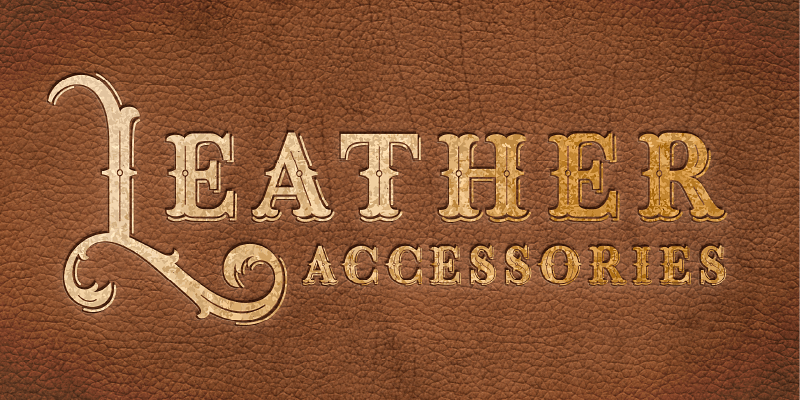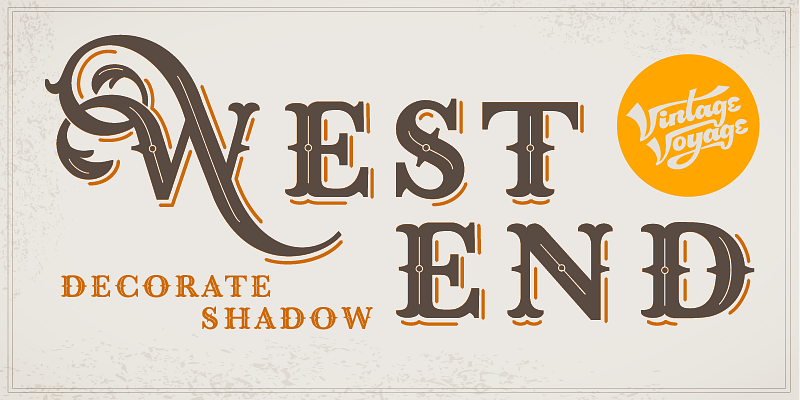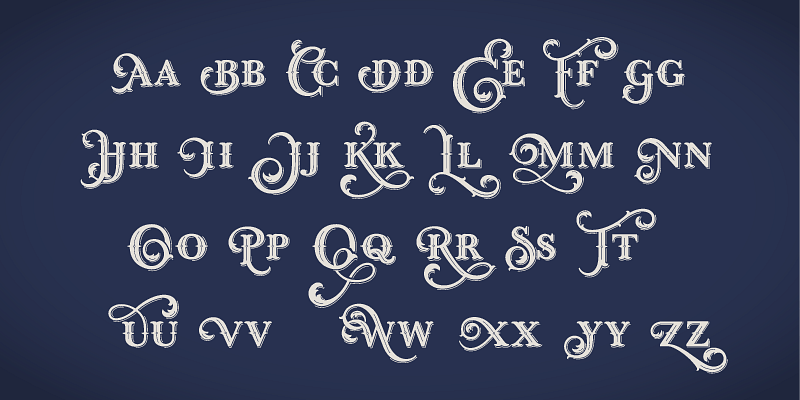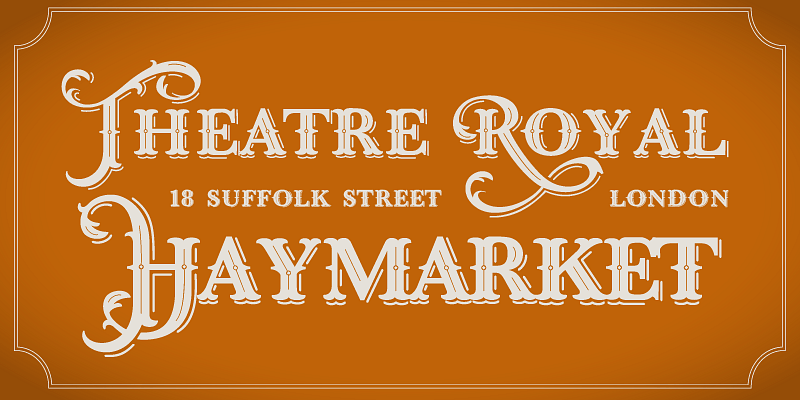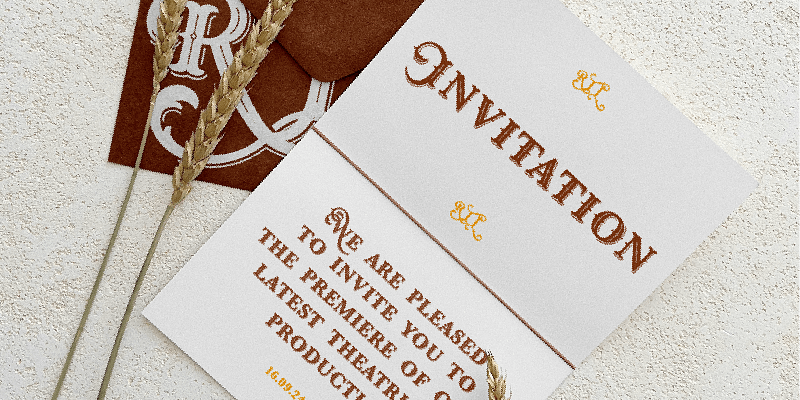
Mise au point par Vintage Voyage Design, West End Decorate Shadow est une police de titrage inspirée des publicités et des enseignes dessinées à la main du début du XXe siècle. Avec ses tiges à bifurcation, sa ligne intérieure décorative, ses ombres subtiles et ses ornements prononcés, elle est parfaite pour une fête sur le thème du western, un décor de pièce de théâtre, un étalage de bonbons à l’ancienne ou tout simplement pour évoquer d’autres temps et d’autres lieux. Empruntez le chemin qui vous ressemble, West End se tient prête pour votre projet décoratif.